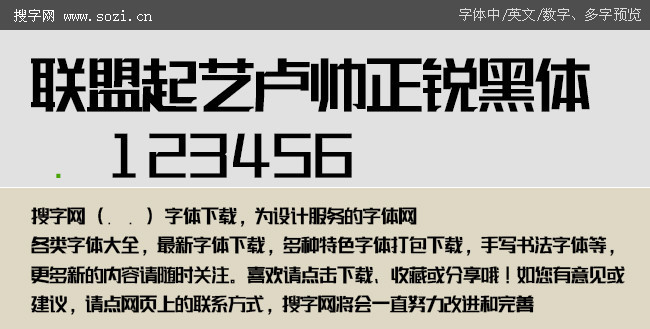
聯(lián)盟起藝盧帥正銳黑體
搜字網(wǎng)提供一款聯(lián)盟起藝盧帥正銳黑體中文藝術(shù)字體下載,聯(lián)盟起藝盧帥正銳黑體是一款非常剛性的免費(fèi)可商用標(biāo)題字體。這款字體筆觸粗實(shí),字形厚重有力,但又不乏設(shè)計(jì)感,整體感覺(jué)非常不錯(cuò)。適用于大標(biāo)題、包裝設(shè)計(jì)、海報(bào)設(shè)計(jì)等應(yīng)用。